心形一般被认作是爱的象征,因为它的模样像颗心脏,怦然心动时的感觉。爱心是由两个半圆形的突出部分拼接在一起的,上凹下尖。所以爱心常常被用在表达爱的场合,包括母爱、父爱,甚至是对宠物的热爱。融入了爱心图案的文字更是增添不少生趣,下面这张 字体图片 给到人的直观感受就是这样的~
这是一款笔画全部由小爱心组成的字体,心形暴击的“汉标爱心体”。构架简洁流畅,充满了单纯可爱的气息。化点为心❤,朝气蓬勃、温婉动人,字里行间都是藏不住的小心心,满满的少女气质~适用于文艺类的书刊、品牌广告和产品包装设计,特别是社交网络的个性化用字引起一阵心形风潮流。
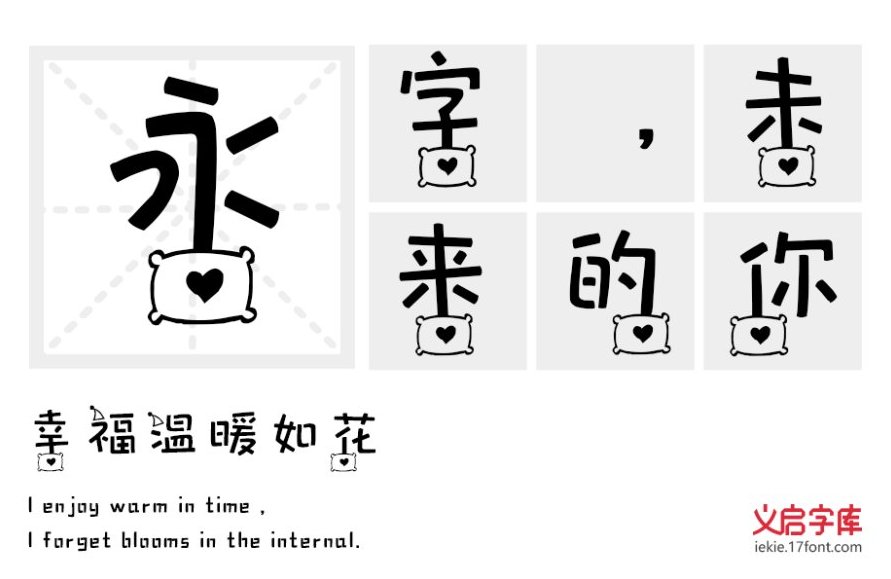
这款“谁偷了我的情书”字体,圆幼的构架好生可爱,字体的下方连接了一个画上了小爱心的情书,借此来表达内心的真挚情谊,深情款款。,在字体的辨认度上也保留了原有的清晰字形,让人可以一眼就看 图片识别字体,还给字体增贴了一种强烈的“印象装饰”。用于广告设计、动漫、封面logo都极其合适。